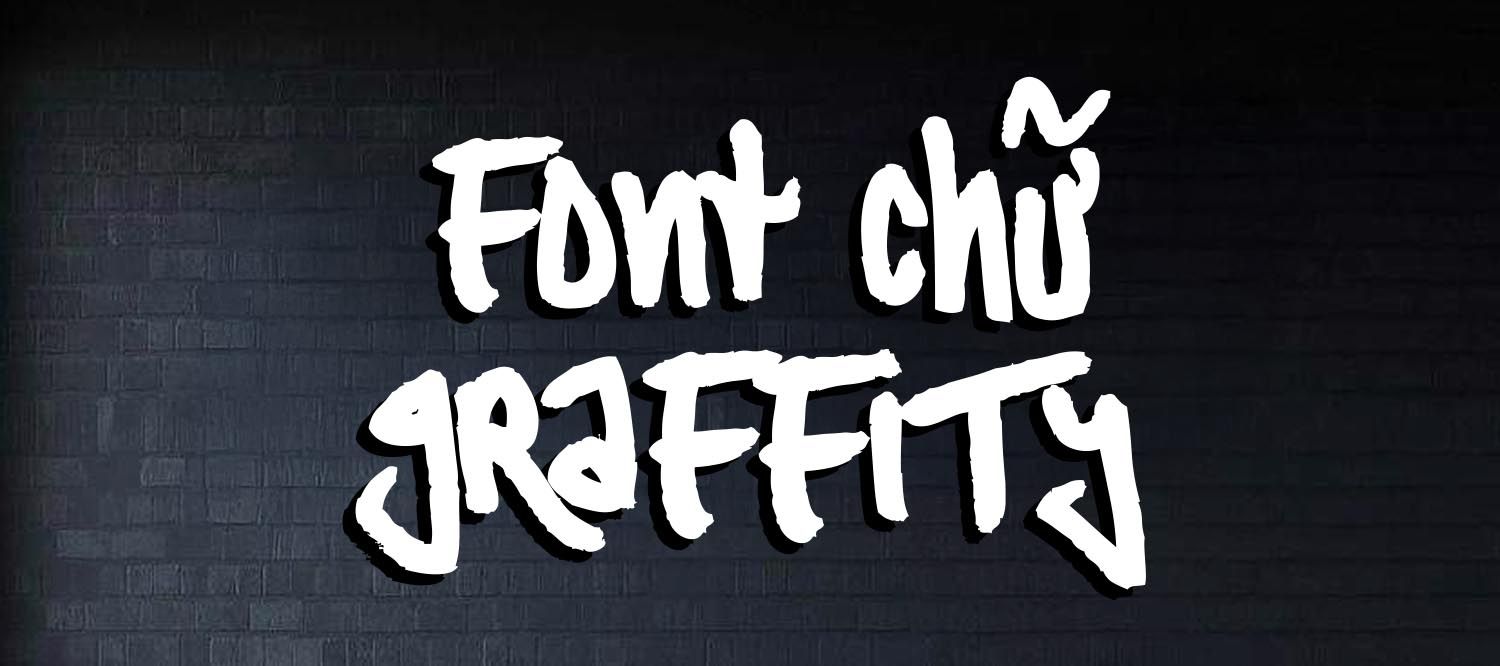
Top 10 font Graffiti Việt hóa hot nhất 2025
Trong thế giới thiết kế sáng tạo, việc lựa chọn font chữ phù hợp đóng vai trò vô cùng quan trọng. Đặc biệt, với những dự án mang phong cách đường phố, năng động và cá tính, font Graffiti Việt hóa đang trở thành lựa chọn hàng đầu của các designer. Bài viết này sẽ giới thiệu đến bạn top 10 font Graffiti Việt hóa hot nhất, giúp bạn dễ dàng tải xuống và áp dụng ngay vào các dự án thiết kế của mình.
Đặc điểm chung của font chữ Graffiti
Font Graffiti ra đời từ văn hóa đường phố, được sử dụng rộng rãi trong nghệ thuật biểu diễn, poster âm nhạc và thiết kế thời trang. Điểm đặc trưng của loại font này là các chữ cái thường được cách điệu, uốn lượn, đôi khi phá cách với những nét đậm, góc cạnh hoặc nhấn mạnh bằng các hiệu ứng 3D, bóng đổ.
Các font Graffiti Việt hóa không chỉ giữ nguyên tinh thần phóng khoáng của Graffiti quốc tế mà còn hỗ trợ đầy đủ ký tự tiếng Việt, giúp designer dễ dàng áp dụng cho các dự án tại Việt Nam. Font Graffiti thường được chia thành nhiều phong cách:
• Phong cách mạnh mẽ, góc cạnh: Thể hiện sự cá tính và nổi loạn.
• Phong cách mềm mại, uốn lượn: Dễ đọc, vẫn giữ được tinh thần nghệ thuật.
• Phong cách kết hợp 3D hoặc hiệu ứng: Tạo cảm giác sống động, hiện đại.
Top 10 font Graffiti Việt hóa nổi bật cho dự án của bạn
Việc lựa chọn font Graffiti Việt hóa phù hợp sẽ giúp dự án của bạn nổi bật, thu hút ánh nhìn và truyền tải thông điệp hiệu quả.
1. Font chữ Graffiti, Hiphop SVN Wrong Hunt Việt hóa
Mô tả: SVN-Wrong Hunt mang phong cách mạnh mẽ, cá tính và bụi bặm, phù hợp cho thiết kế poster, bìa album, banner hoặc các sản phẩm streetwear. Kiểu chữ gợi nhớ đến nghệ thuật đường phố, thể hiện tinh thần tự do, phóng khoáng và nổi loạn của hiphop.
2. Font chữ Việt hóa phong cách Graffiti SVN Skill
Mô tả: SVN Skill mang đến vẻ ngoài mềm mại nhưng không kém phần cá tính, mạnh mẽ và đậm chất đường phố. Với những nét vẽ phóng khoáng, uốn lượn tự do, font này rất phù hợp để thiết kế poster, bìa album, banner hay các sản phẩm sáng tạo dành cho giới trẻ.
3. Font chữ phong cách Graffiti TH Typographic Onedalism Việt hóa
Mô tả: TH Typographic Onedalism là font chữ mang phong cách viết tay đậm chất đường phố, với nét bút mạnh mẽ nhưng vẫn tự nhiên và phóng khoáng. Các ký tự có xu hướng thu hẹp chiều ngang, gợi cảm giác viết nhanh bằng cọ hoặc chổi sơn. Tổng thể, font toát lên tinh thần nổi loạn, góc cạnh và đầy cá tính, rất phù hợp cho các thiết kế cần sự khác biệt, mạnh mẽ và ấn tượng.
4. Font chữ phong cách Graffiti Việt hóa TH Jaylene
Mô tả: TH Jaylene mang dáng dấp Graffiti hiện đại với chữ cái dày, bo tròn, gợi liên tưởng đến nét phun sơn trên tường. Đường nét liền mạch, hơi nghiêng cùng độ nảy tinh tế tạo cảm giác chuyển động mượt mà. Mỗi ký tự như thấm đẫm tinh thần hiphop, thể hiện sự tự do, sáng tạo và cá tính nổi loạn của nghệ thuật đường phố.
5. Font chữ brush nét cọ chủ đề halloween SVN Another Danger
Mô tả: SVN Another Danger là font chữ brush nét cọ đậm chất Halloween, mang lại cảm giác bí ẩn và mạnh mẽ. Những vết mực ngẫu hứng trong từng ký tự gợi nên phong cách retro, hardcore, vừa hoang dại vừa sáng tạo. Đây là lựa chọn lý tưởng cho các thiết kế nghệ thuật mang màu sắc hỗn loạn, độc đáo.
Tác giả gốc: The Branded Quotes
Tác giả Việt hóa: STYLEno.1 Fonts
6. Font chữ tiếng Việt kiểu brush SVN Road Rage
Mô tả: SVN Road Rage mang phong cách mạnh mẽ, phóng khoáng và đầy cá tính. Đây là lựa chọn tuyệt vời cho những thiết kế cần sự nổi bật như poster, tiêu đề, logo hoặc ấn phẩm quảng cáo. Với đường nét tự do và hiệu ứng cọ vẽ độc đáo, Road Rage giúp tác phẩm của bạn trở nên ấn tượng và thu hút ngay từ cái nhìn đầu tiên.
Tác giả gốc: Youssef Habchi
Tác giả Việt hóa: STYLEno.1 Fonts
7. Font chữ hiphop Việt hóa TH Queen Rocker
Mô tả: TH Queen Rocker là font chữ hiphop táo bạo, mang tinh thần nổi loạn với nét vẽ mạnh mẽ và kết cấu thô ráp. Font đem lại phong cách hiện đại, trẻ trung, tràn đầy năng lượng cho thiết kế. Được S99.VN Việt hóa đầy đủ bộ ký tự và hỗ trợ mã hóa PUA, TH Queen Rocker giúp bạn dễ dàng sử dụng mọi biến thể.
8. Font chữ hiphop Việt hóa SVN Evitrian
Mô tả: Evitrian là font chữ hiển thị mạnh mẽ, mang hơi thở đô thị hiện đại. Với nét chữ độc đáo và cá tính, nó giúp thiết kế của bạn luôn nổi bật và dễ gây ấn tượng. Font này rất linh hoạt, phù hợp cho nhiều nhu cầu sáng tạo như: Logo, Sticker, ghi chú, thiệp mời, Brochure và nhiều ấn phẩm khác.